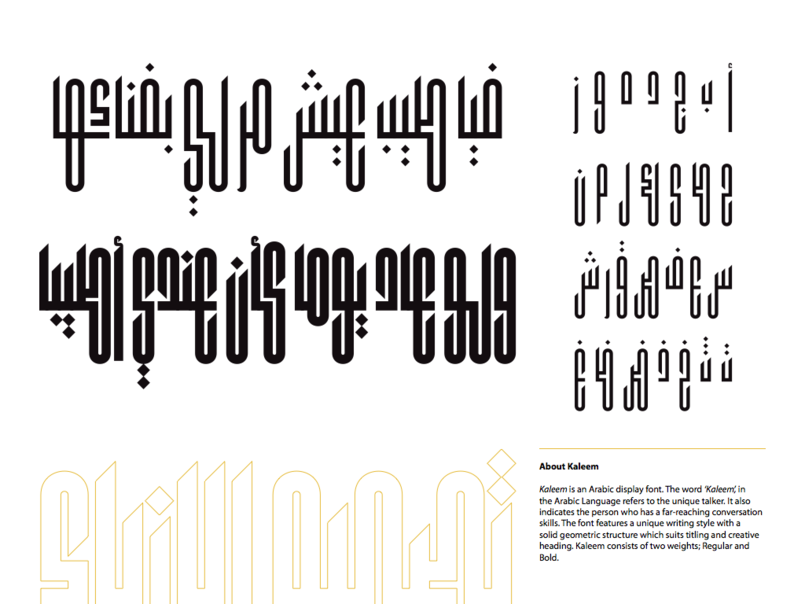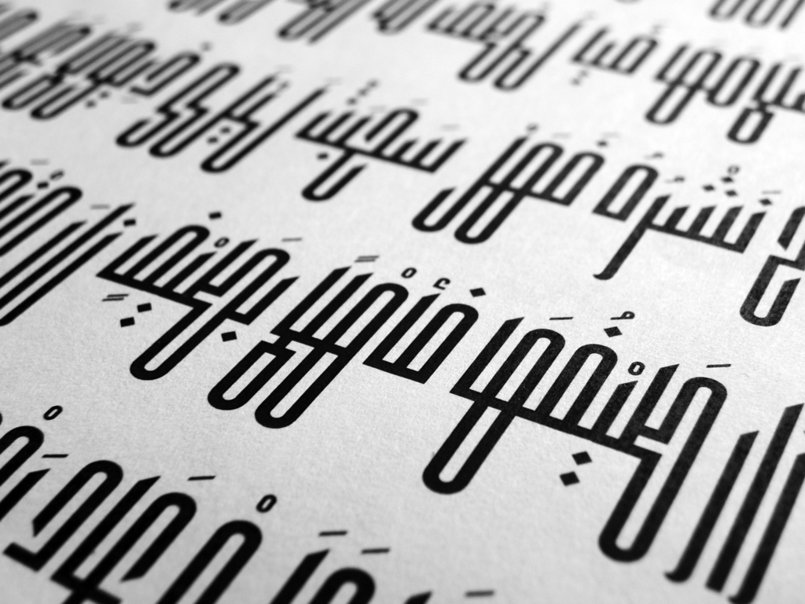
Kaleem, Arabic Font | كَليم- خط عربي
.كليم هو خط عربي ذو بنية هندسية مستطالة وفريدة من نوعها الخط يناسب مختلف التطبيقات بما فيها الطباعة والعرض الرقمي ومتاح بوزنين؛ العادي والسميك الخط متاح هنا mostafa-abasiry.com/kaleem Kaleem is an Arabic display font. The word ‘Kaleem’, in the Arabic Language refers to the unique talker. It also indicates the person who has a far-reaching conversation skills. The font features a unique writing style with a solid geometric structure which suits titling and creative heading. Kaleem consists of two weights; Regular and Bold.
كليم - خط عربي
مرادفات الحروف في خط كليم
تصميم العناوين والأيقونات مع كليم
اوزان كليم
Contextual Alternates
اوزان كليم مع الحروف البديلة Contextual Alternates
كليم - وزن عادي
كليم - وزن سميك